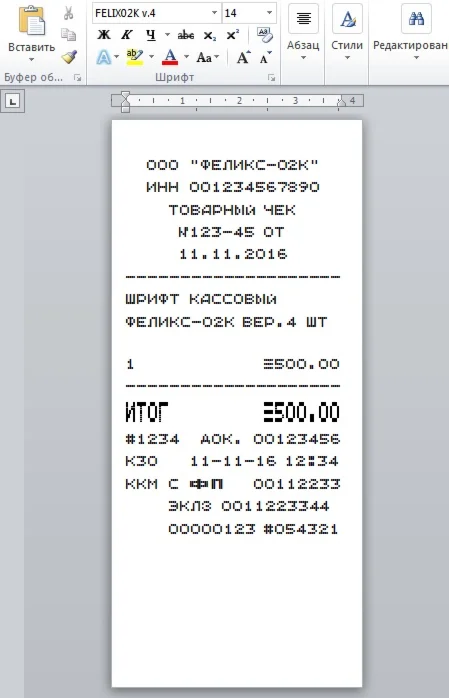
Шрифт кассового аппарата ФЕЛИКС-02К (версия 5х6 точек) в формате TTF (русские и английские буквы) для использования в программе Microsoft Word. В архиве находятся стандартный и высокий шрифты в формате TTF и шаблон чека. Вам остается только установить шрифты в систему (обычно C:\WINDOWS\Fonts), открыть шаблон и начать редактирование. Печатать чеки предпочтительно на термопринтере, на кассовой термоленте. Хотя можно печатать и на струйнике и лазерном, с возможностью вывода на факсовую бумагу. Лучшее качество, естественно, при печати на термопринтерах.